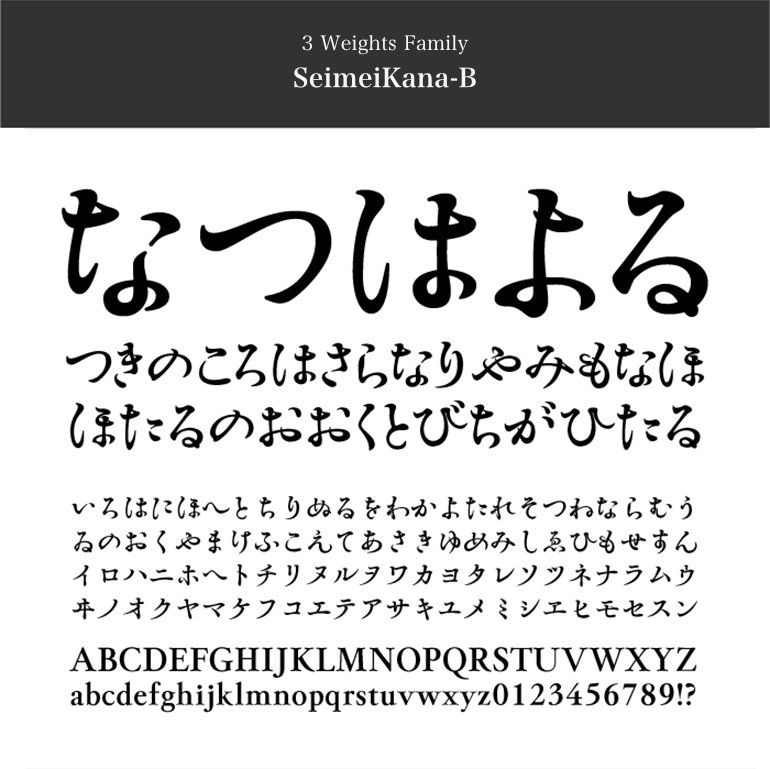
3. REN FONT / タイポグラフィクス蓮
REN FONT Typographics REN
日本タイポグラフィ協会主催作品展「年鑑」で
入選を重ねる高品質のフォント
タイプデザイナー・金井和夫氏が創り出すフォントは日本の伝統美を意識した特徴的なフォント。なかでも「和音」ファミリーは、漢字、平仮名、片仮名、欧文、記号類、用途字種、数字の各字種に音楽的特徴をもたせ、それぞれがもつ個性が見事に調和する「和音=ハーモニー」の名にふさわしい書体です。店頭販促POPから本文書体組まで幅広く使用できる完成度の高いフォントです。また、勢蓮明朝ファミリー・勢蓮呉竹ファミリーは、文字がもつ本来の美しさを極限まで追求した傑作です。細めのウェイトでは華奢さを、太めのウェイトでは大胆さを与え、全ウェイトに共通する文字の流れの流麗さが高級感を演出してくれるフォントです。
新書体「清明かな OTF」
優しさと切れ味をあわせ持つ清明かなOTF 3WeightsFontFamily
清々(すがすが)しい明朝という意味も込めています。この書体は、当社タイプデザイナー金井和夫の普段使いの文字をベースとした、明兆・行書・楷書の複雑なフィルムイメージを持っています。「R(レギュラー)」、「M(ミディアム)」、「B(ボールド)」の合計3ウェイトで構成されているます。また、オールドなイメージものこしつつもその概念にとらわれず大仮名に設計してあるので、近代的な組版にも対応するマルチな性格を備えています。特徴が強いので、長文には向きませんが、短い本文組みや、ちょっとした見出しに使ってみてください。躍動感に満ちた、訴求力のある紙面になるはずです。縦組、横組ともプロポーショナル加工を加えました。ペアカーニングもほどこしてあります。
可読性に優れ、勢いと優雅さを兼ね備えた勢蓮明朝仮名ClassicOTF 8WeightsFontFamily
相反する、勢いと優美さを融合した手書き風かな明朝。勢蓮明朝仮名Classicファミリーの各書体は2001年度特定非営利法人タイポグラフィ協会により開催された「日本タイポグラフィ年間2001」コンテストの書体部門入選作「勢蓮明朝-M」をブラッシュアップし、多ウェイト化の上、付属欧文・約物・記号類を追加したものです。
勢蓮明朝仮名ClassicOTF。この書体は、当社タイプデザイナー金井和夫の普段使いの文字をベースとした、明朝・行書・楷書の複雑なフォルムイメージを持っています。最細ウェイト「L(ライト)」から最太ウェイト「U(ウルトラ)」までの、合計8ウェイトで構成されています。また、オールドなイメージを残しつつも、その概念に囚われず大仮名に設計してあるので、近代的な組板にも対応するマルチな性格を備えています。筆致に勢いがあり、その勢いを活かしながら流麗にリズムを刻むプロポーション。見出し書体として十分なインパクトを与えることができるほか、本文の書体としても利用が可能なそのフォルムは可読性に優れつつ、組みを行ったときに盤面に独自な勢いと優雅さを与えます。
特徴
両仮名。明朝体の形状を基本にしていますが、行書・楷書のイメージも含んでいます。作者の普段使いの文字をアレンジしてあるので、明朝のセオリーを外した筆勢も随所にあり、強い個性と主張を発揮します。起筆や払い、跳ねの細い先端は、丸く処理してあることでソフトさもさりげなく持ち合わせています。文字の高さや横幅がフォントの概念を覆すほどバラエティに富んでいるので、一文字づつバラしてサイズに強弱をつけると、見出しとしてあたかも書道のような最大限の効果を得られます。また本文組にも既存の漢字と組み合わせてよく調和します。
ウェイト
ウェイトの図
組見本
ウェイト別見本 EL,L,R,M,DB,B,H,U